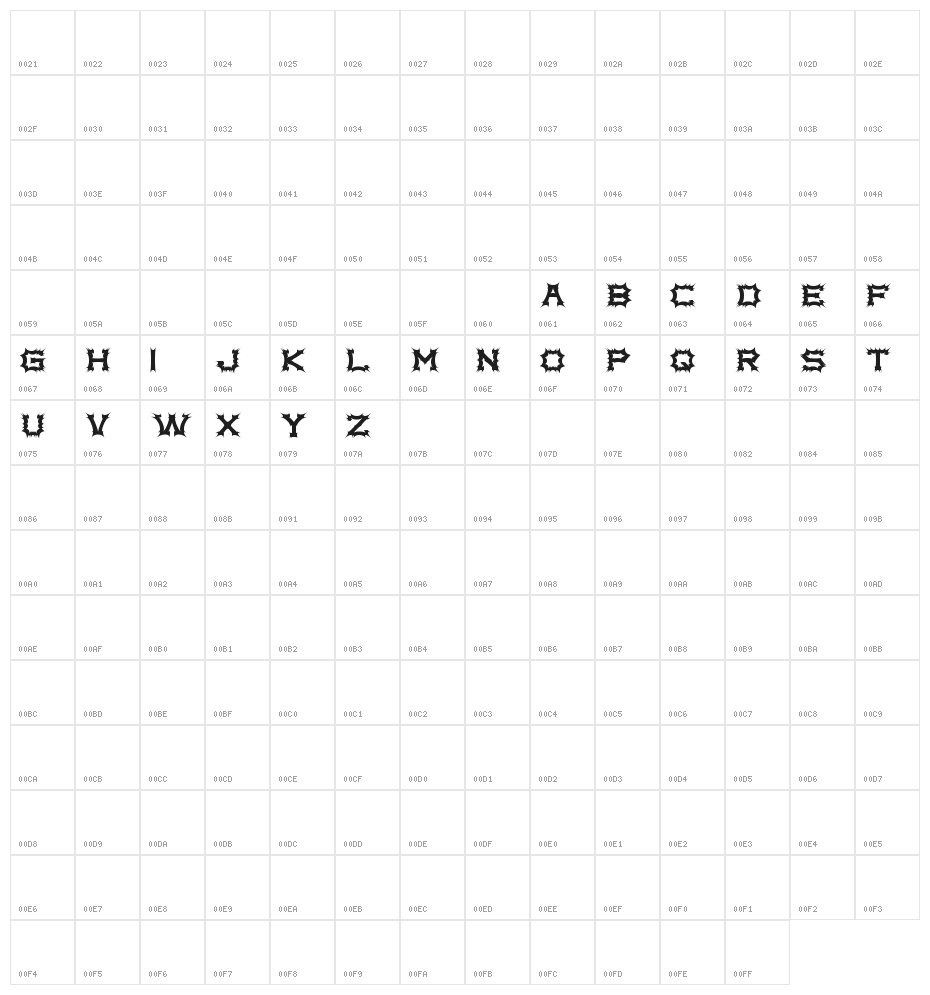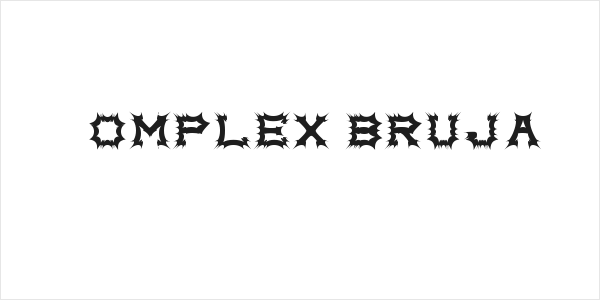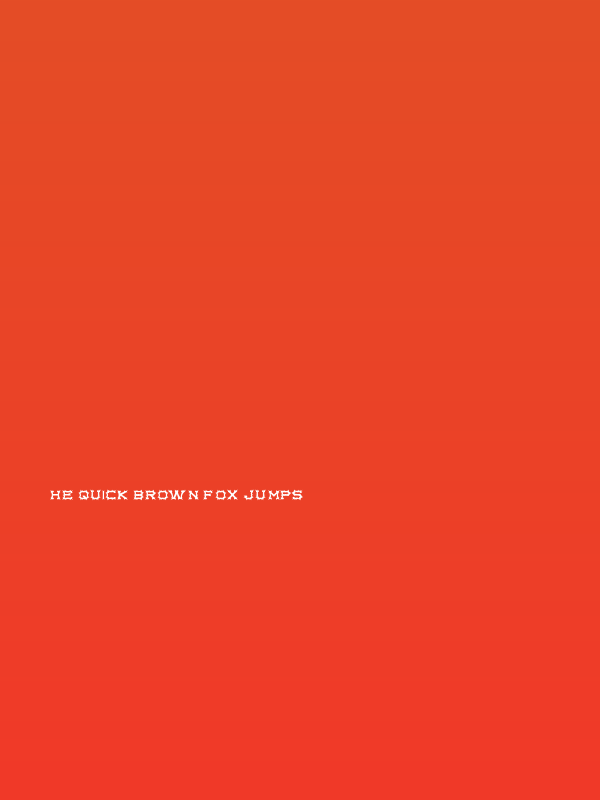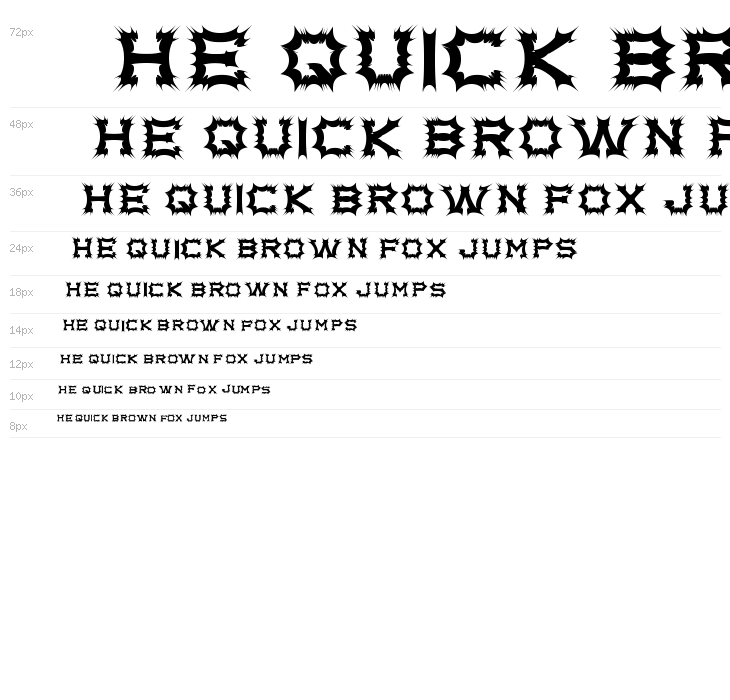
Complex bruja Font
| Gesamtstil | Gothic, Decorative |
| Vorgeschlagene Projekte | Ideal for Halloween-themed designs, fantasy book covers, gothic event invitations, and edgy branding projects. |